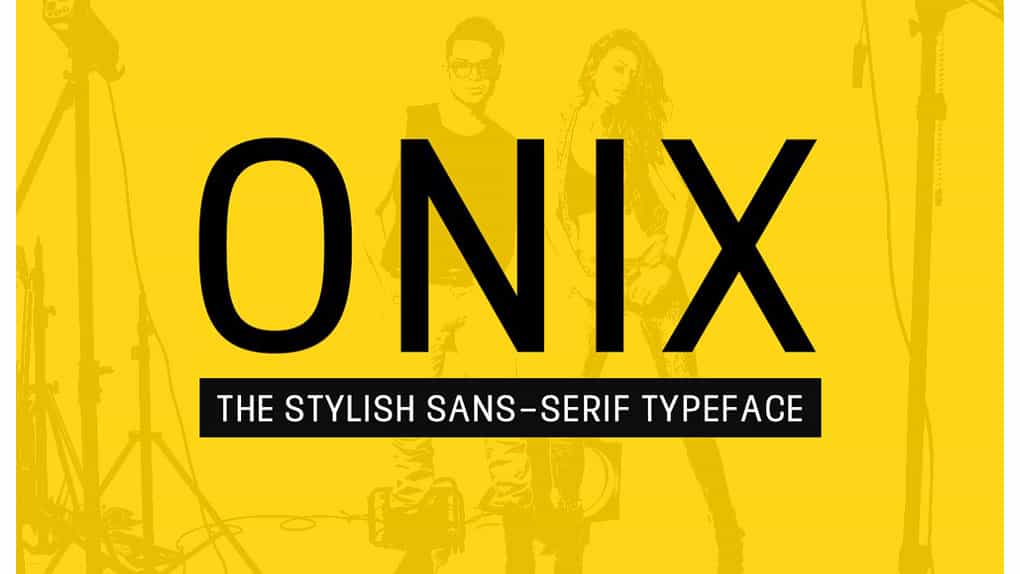
فونت انگلیسی ONIX : ONIX یک نوع فونت انگلیسی متن مدرن با سبک و هویت منحصر به فرد خود است. این فونت از برخی سبک های بسته بندی و حروف محصول غربی الهام گرفته شده است. ONIX میتواند برای ارائه عناوین شگفت انگیز، متن زیرنویس جذاب، انواع لوگو های حرفه ای، برچسب های بسته بندی محصولات، برندهای پوشاک مد، سبک های وب سایت مدرن و هر آنچه تصور کنید مورد استفاده قرار گیرد.